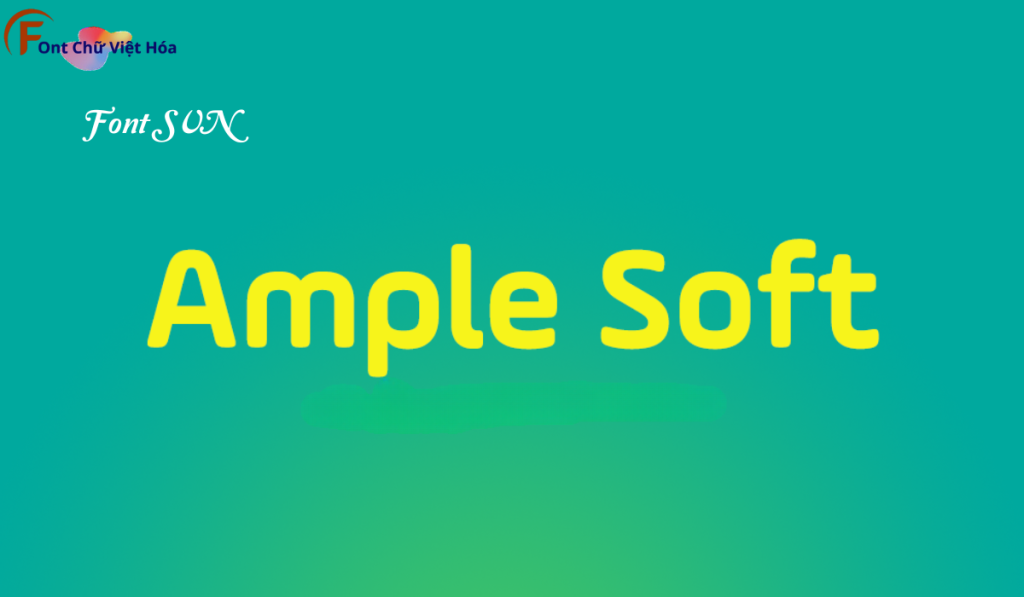
Ample Font SVN Việt Hóa
Kiểu chữ: Có chân
Ample Font SVN Việt Hóa là một font chữ không chân mạnh mẽ, thuộc bộ font SVN. Được thiết kế với mục tiêu mang lại sự nổi bật và ấn tượng, font này lý tưởng cho các dự án thiết kế như tiêu đề, quảng cáo, và bao bì sản phẩm. Với các nét chữ đậm và chắc chắn, Ample Font SVN Việt Hóa không chỉ dễ đọc mà còn tạo cảm giác mạnh mẽ và quyết đoán. Việc Việt hóa font giúp người dùng dễ dàng sử dụng trong các thiết kế tiếng Việt, mang lại sự tiện lợi và thẩm mỹ cao.